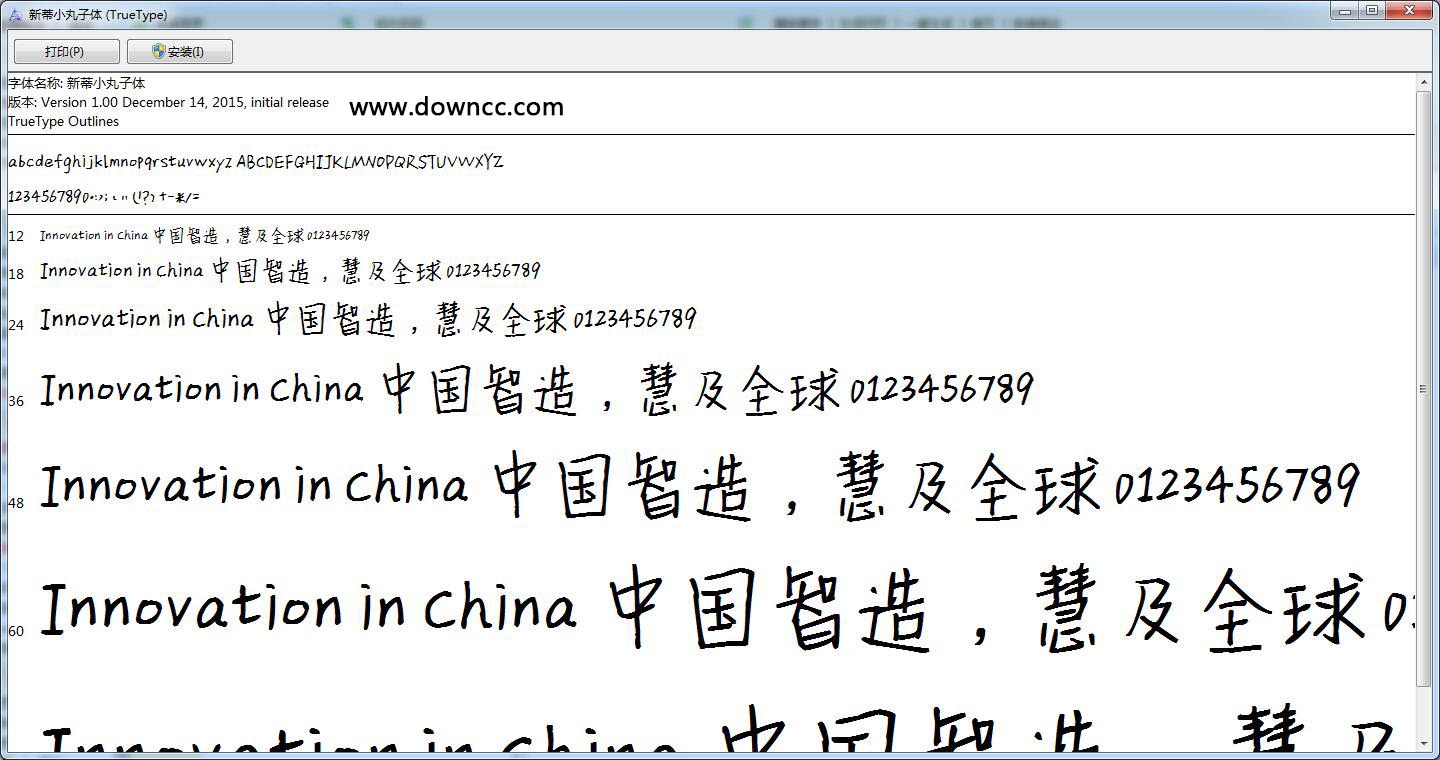
新蒂小丸子體高級(jí)版是一款美工字體工具!這款字體總體看起來(lái)比較柔美出眾,用戶可以用來(lái)進(jìn)行平面設(shè)計(jì)、網(wǎng)站設(shè)計(jì)使用!歡迎用戶來(lái)綠色資源網(wǎng)下載!
新蒂小丸子體高級(jí)版是由新蒂字體官網(wǎng)推出的美工方面的設(shè)計(jì)字體應(yīng)用,字體整體上細(xì)膩柔美,整體上效果十分出眾,可以應(yīng)用于廣告設(shè)計(jì)、平面設(shè)計(jì)、印刷包裝、藝術(shù)設(shè)計(jì)、網(wǎng)站設(shè)計(jì)領(lǐng)域。